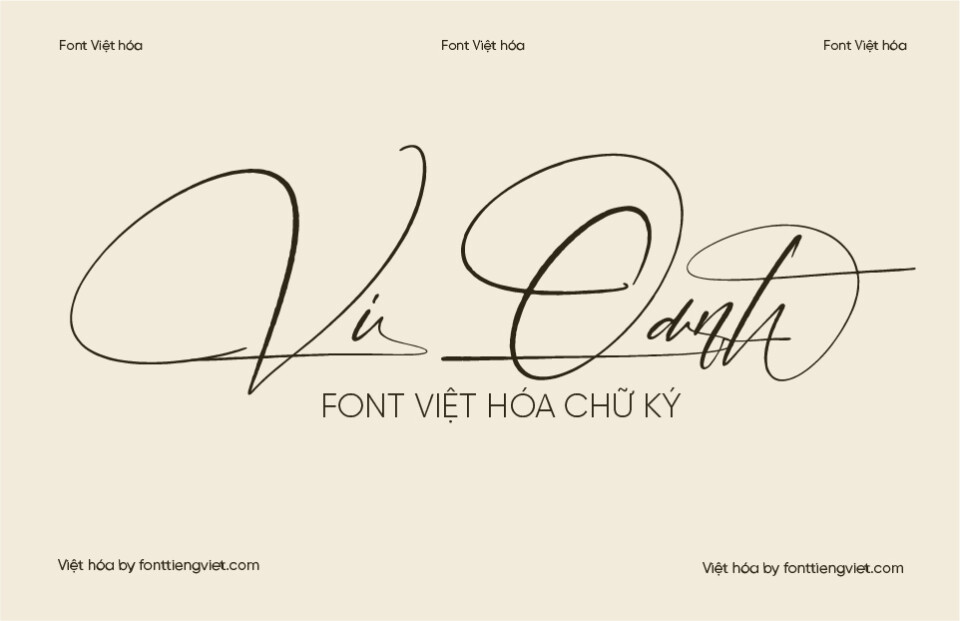
Font Việt hóa 1FTV VIP Molahesta Italic – Font việt hóa chữ ký cho thiết kế chuyên nghiệp
Nếu bạn đang tìm kiếm một bộ Font Chữ mang đậm phong cách cá nhân và nghệ thuật, Font Việt hóa 1FTV VIP Molahesta Italic – Font việt hóa chữ ký chính là sự lựa chọn hoàn hảo. Đây là mẫu phông chữ được thiết kế tinh xảo, mô phỏng những nét bút ký mềm mại nhưng không kém phần quyết đoán, giúp nâng tầm giá trị thẩm mỹ cho mọi dự án sáng tạo của bạn.
Khám phá đặc điểm nổi bật của Font Việt hóa 1FTV VIP Molahesta Italic – Font việt hóa chữ ký
Nét chữ thanh thoát và hiện đại
Molahesta Italic gây ấn tượng bởi những đường nét uốn lượn tự nhiên, tạo cảm giác như được viết tay trực tiếp. Đặc biệt, bản Việt hóa này đã được tối ưu hóa hoàn toàn để hiển thị các dấu tiếng Việt một cách mượt mà nhất, không bị lỗi font hay mất nét khi soạn thảo trên các phần mềm đồ họa phổ biến.
Tính ứng dụng linh hoạt trong sáng tạo
Nhờ vào vẻ đẹp sang trọng, Font Việt hóa 1FTV VIP Molahesta Italic – Font việt hóa chữ ký thường xuyên được các nhà thiết kế tin dùng cho việc làm logo thương hiệu, thiết kế thiệp cưới, banner quảng cáo cao cấp hoặc tạo chữ ký cá nhân trên ảnh. Độ nghiêng đặc trưng của phong cách Italic tạo ra sự chuyển động thị giác, mang lại cảm xúc sâu sắc cho người xem.
Lợi ích khi sử dụng Font Việt hóa 1FTV VIP Molahesta Italic – Font việt hóa chữ ký
Việc sở hữu một phông chữ chất lượng giúp bài trình bày hoặc sản phẩm của bạn trở nên chuyên nghiệp hơn. Molahesta Italic không chỉ dễ đọc mà còn tạo dấu ấn riêng biệt giữa hàng ngàn font thông dụng khác. Đối với cộng đồng thiết kế tại Việt Nam, đây là công cụ đắc lực để biến các ý tưởng khô khan thành những tác phẩm nghệ thuật sống động. Hãy trải nghiệm ngay sức hút từ bộ Font Miễn Phí, Font Việt Hóa, Font Việt hóa 1FTV VIP Molahesta Italic – Font việt hóa chữ ký để hoàn thiện bộ sưu tập của mình.